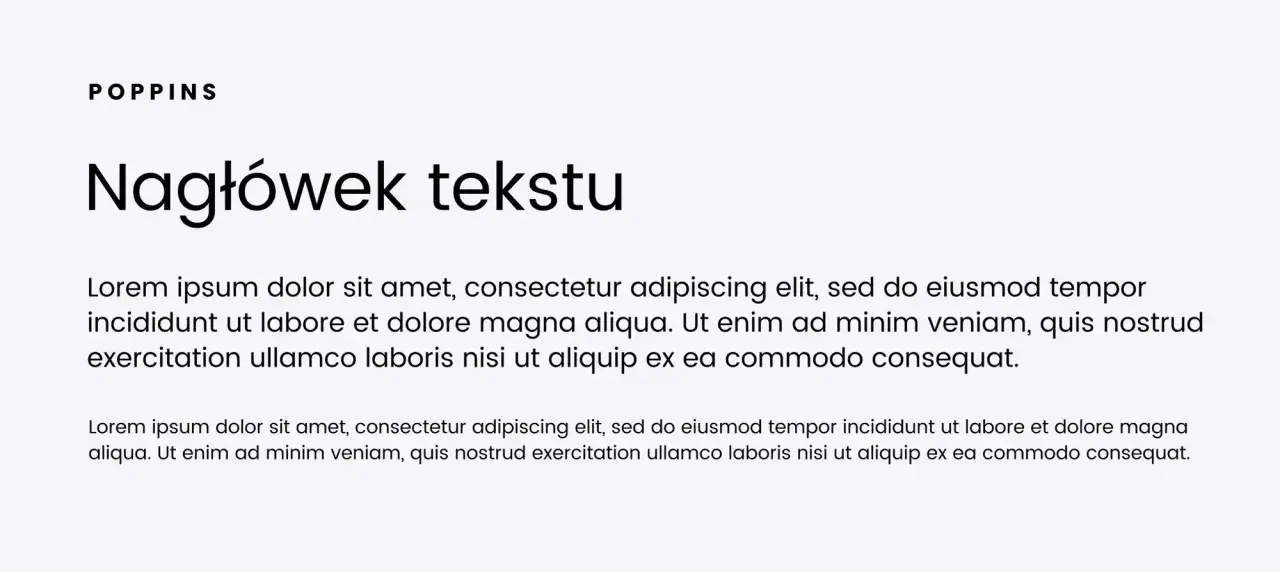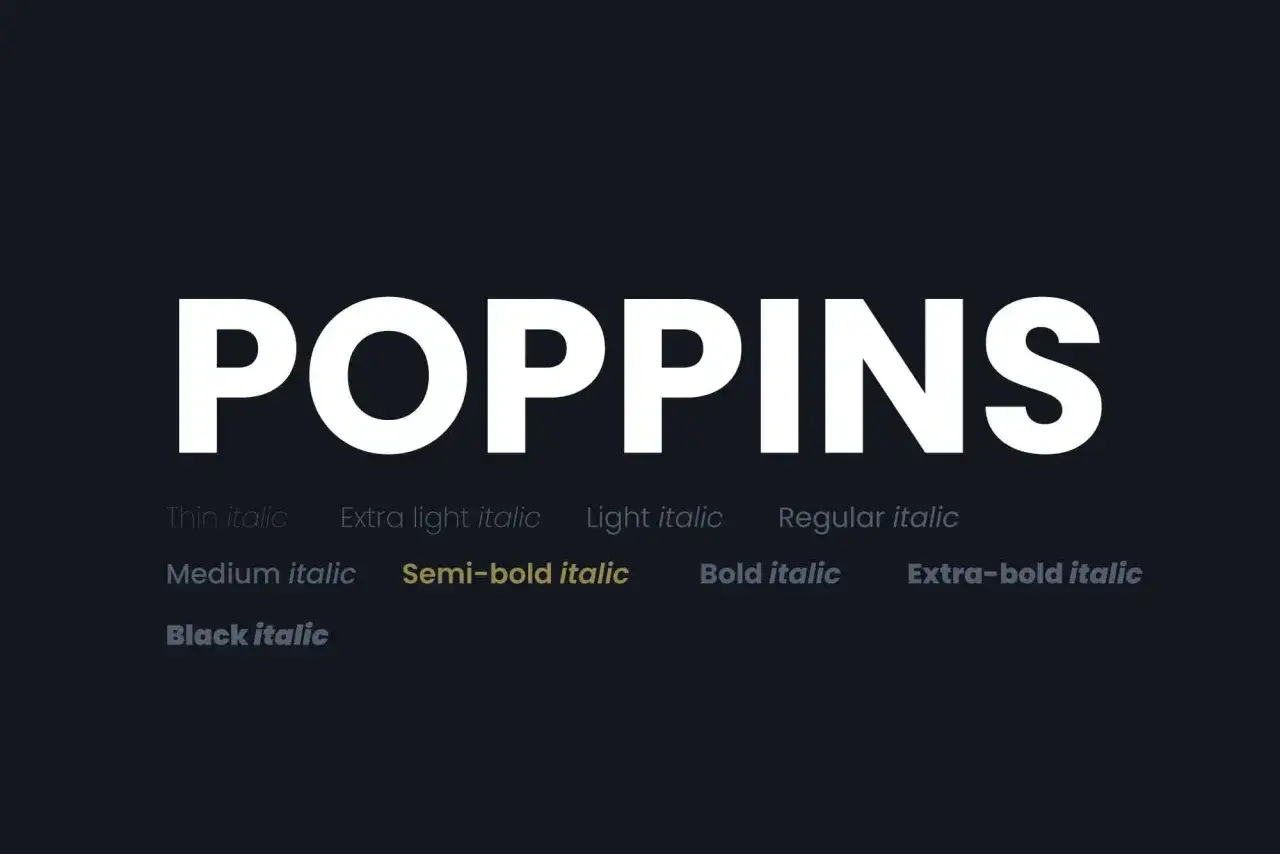
Czcionka Poppins - Kiedy działa, z czym łączyć i jak jej nie zepsuć?
Nagłówek "Nagłówek tekstu" i tekst demonstracyjny w czcionce Poppins.
Czcionka Poppins to geometryczny bezszeryfowy krój, który bardzo często trafia do identyfikacji marek, stron internetowych i aplikacji. W tym tekście pokazuję, skąd bierze się jej popularność, kiedy naprawdę pomaga w typografii, z czym ją łączyć i gdzie łatwo przesadzić z efektem „ładnie, ale bez charakteru”.
Najważniejsze rzeczy o Poppins w jednym miejscu
• Poppins to krój geometryczny, więc daje nowoczesny, czysty i uporządkowany efekt.
• Dobrze działa w nagłówkach, UI i materiałach marketingowych, zwłaszcza tam, gdzie liczy się prostota.
• W dłuższych akapitach wymaga większej uwagi niż w headline’ach, bo zbyt mały rozmiar szybko obnaża słabą hierarchię.
• Najlepiej łączyć ją z krojem, który wnosi kontrast: klasycznym szeryfem albo spokojnym sans-serifem do tekstu.
• Najczęstszy błąd to używanie Poppins wszędzie, bez różnicowania wag, odstępów i ról w projekcie.
Dlaczego Poppins tak dobrze działa w projektach cyfrowych
Ja zwykle traktuję Poppins jako krój, który daje projektowi porządek bez zbędnej formalności. Jej geometryczna konstrukcja sprawia, że litery wyglądają równo, nowocześnie i przewidywalnie, a to w interfejsach jest dużą zaletą: użytkownik nie musi „rozgryzać” kroju, tylko od razu czyta treść.
W praktyce ważne są trzy rzeczy. Po pierwsze, prosta bryła liter dobrze skaluje się w nagłówkach i elementach interfejsu. Po drugie, Poppins ma wystarczająco czyste formy, żeby nie wyglądać ciężko nawet w mocniejszych wagach. Po trzecie, dobrze znosi polskie znaki, więc nadaje się do lokalnych projektów bez kombinowania z zamiennikami.
To krój, który szczególnie dobrze odnajduje się w projektach wymagających świeżości, ale bez agresywnego charakteru. Jeśli marka ma mówić „jesteśmy nowoczesni i poukładani”, Poppins robi to bardzo sprawnie. Jeśli ma krzyczeć, prowokować albo budować wyraźnie redakcyjny klimat, trzeba już uważać. To prowadzi do pytania, w jakich zastosowaniach naprawdę pokazuje swoją siłę, a gdzie jego neutralność bywa ograniczeniem.
Gdzie ta rodzina wygląda najlepiej w praktyce
Poppins najlepiej pracuje tam, gdzie typografia ma wspierać czytelność i poczucie ładu. Najczęściej widzę ją w landing page’ach, produktach SaaS, prezentacjach ofertowych, prostych identyfikacjach wizualnych i w social mediach, gdzie krój musi być czytelny na małym ekranie i jednocześnie wyglądać estetycznie w dużym nagłówku.
Zastosowanie Co daje Na co uważać
Landing page Mocny, czysty headline i dobra hierarchia CTA Bez kontrastu z innym krojem całość może wydać się zbyt przewidywalna
Aplikacja / UI Spójny wygląd komponentów i czytelne etykiety Zbyt dużo wag i wersalików szybko robi wizualny szum
Branding nowoczesny Wrażenie prostoty, technologii i porządku W markach premium może zabraknąć głębi albo elegancji
Materiały do social mediów Dobra czytelność w krótkich komunikatach W długich tekstach wymaga solidnego odstępu między liniami
Artykuły i treści redakcyjne Jasna struktura śródtytułów i wyróżnień Nie zawsze jest najwygodniejsza jako główny krój długiego tekstu
W tym miejscu zwykle robię prosty test: jeśli krój ma budować „pierwsze wrażenie” projektu, Poppins sprawdza się dobrze. Jeśli ma nieść czytelnika przez długie akapity, zaczynam patrzeć na konkurencyjne kroje z większą ostrożnością. Właśnie dlatego warto myśleć o niej nie jako o uniwersalnym rozwiązaniu, tylko o jednym z narzędzi w szerszym systemie typograficznym.
Wizualizacja rodziny czcionek Poppins, prezentująca różne grubości i kroje pisma, od cienkiego po czarny.
Z czym łączyć Poppins, żeby zachować kontrast i rytm
Najbezpieczniejsze zestawienia opierają się na kontraście. Poppins jest geometryczna i równa, więc dobrze zyskuje wtedy, gdy druga czcionka wnosi trochę innego temperamentu. Ja najczęściej wybieram jeden z trzech kierunków.
Cel połączenia Dobry kierunek Dlaczego to działa
Więcej elegancji Klasyczny szeryf do tekstu, np. Merriweather albo Source Serif 4 Szeryf daje kontrast, a Poppins zostaje nowoczesnym akcentem w nagłówkach
Spójny produkt cyfrowy Neutralny sans-serif do body, np. Inter lub DM Sans Oba kroje są czytelne, ale różnią się charakterem na tyle, by nie zlewać się w jedną masę
Techniczny klimat Monospace dla danych, kodu albo tabel pomocniczych Monospace porządkuje liczby i podbija wrażenie systemowości
W typografii często pada słowo tracking, czyli ogólny rozstrzał odstępów między literami. Przy Poppins nie przesadzam z jego zwiększaniem, bo krój już sam z siebie jest dość regularny. Z kolei kerning, czyli korekta odstępu między konkretnymi parami liter, warto sprawdzić zwłaszcza w nagłówkach i logotypowych zapisach, bo to właśnie tam najbardziej widać drobne błędy.
Jeśli projekt ma być wyrazisty, ale nie chaotyczny, takie zestawienie daje dużo lepszy efekt niż użycie dwóch podobnych bezszeryfowych krojów. Z tego miejsca naturalnie przechodzę do rzeczy, które najczęściej psują odbiór Poppins w praktyce.